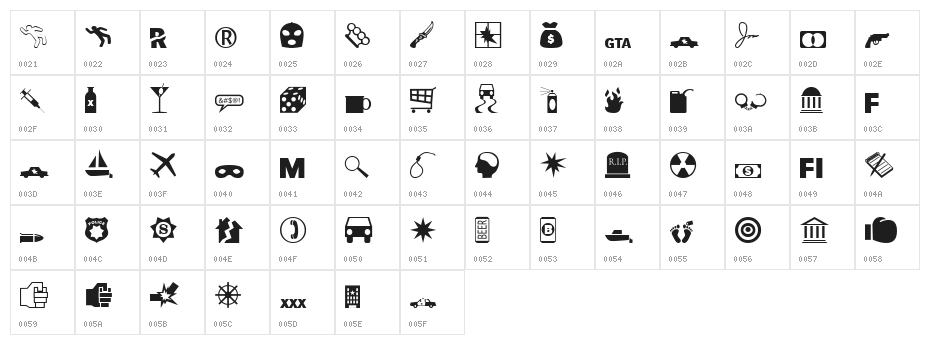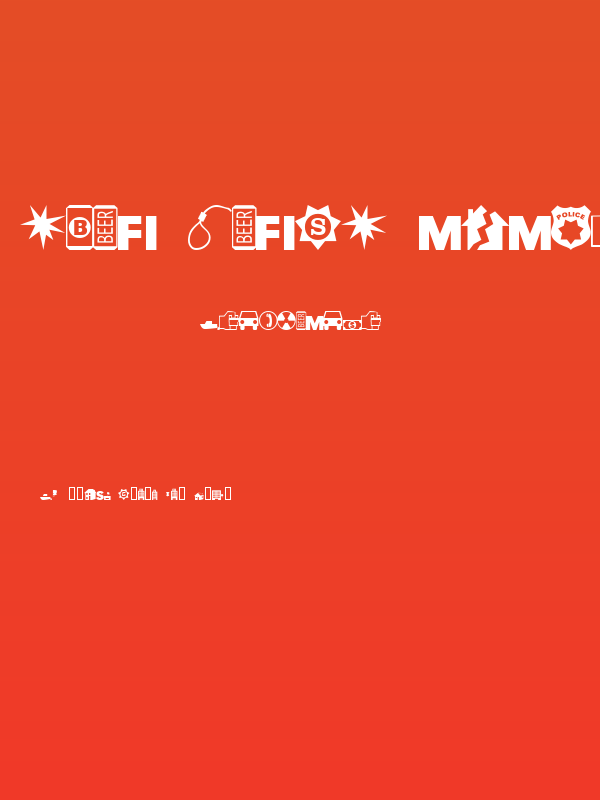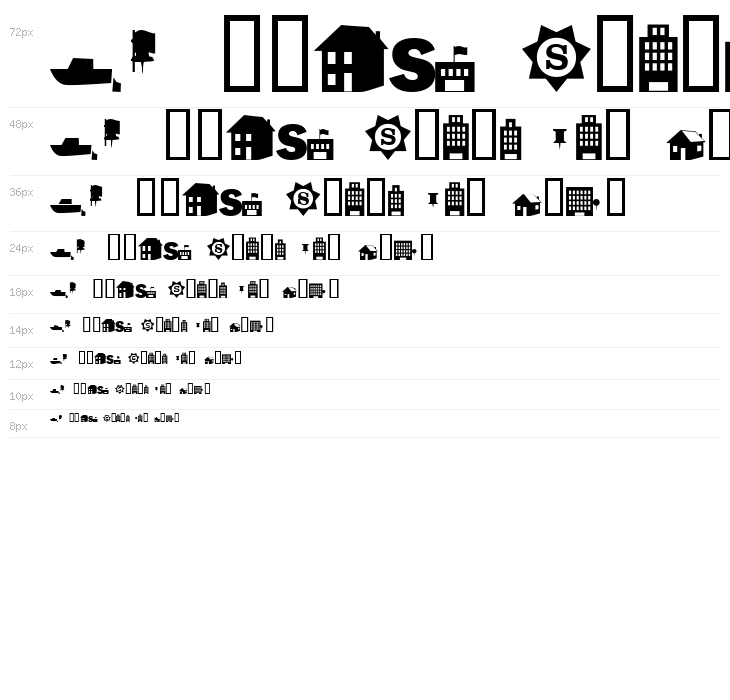
ESRI Crime Analysis Font
| Anwendungsfall | Logos, Thematic designs, Infographics |
| Vorgeschlagene Projekte | Ideal for crime-related infographics, educational materials on law enforcement, or thematic design projects requiring illustrative symbols. |